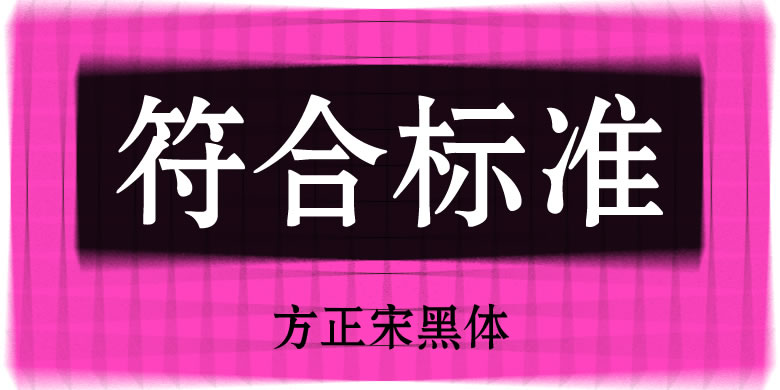
方正宋黑
在宋体字的结构中,融入黑体粗壮稳重的特点,故名“宋黑”。宋黑的初始设计来源于1965年上海印刷技术研究所徐学成的铅字设计稿,原稿只有4200字,数字化后进行了扩充。虽源于20世纪60年代,但字形风格却不受时代影响,仍常用于当代各类文化语境。方正宋黑体笔形朴拙、传统,由于横竖笔画粗细接近,具有类似黑体的远视距效果,在屏幕显示上的表现也很出色,醒目凝重。